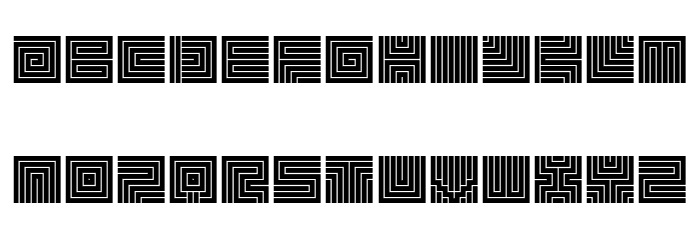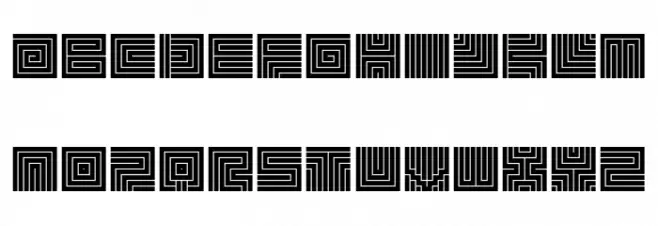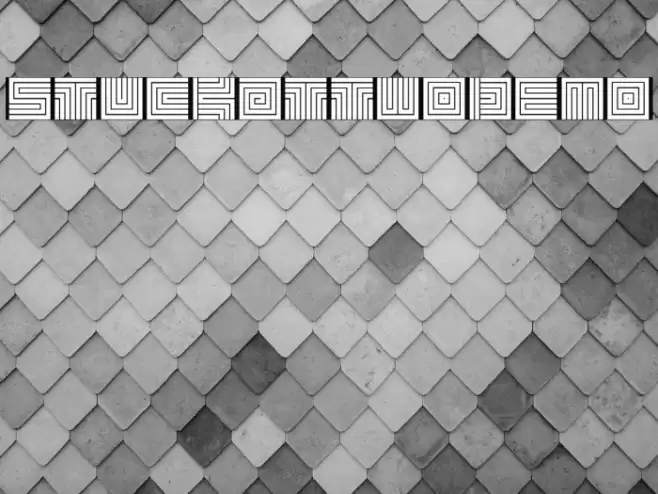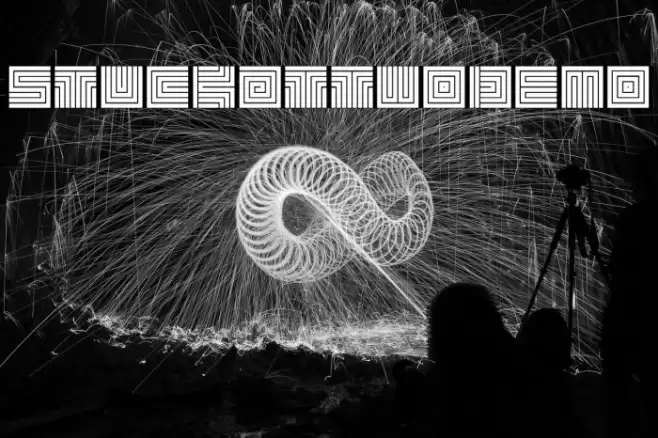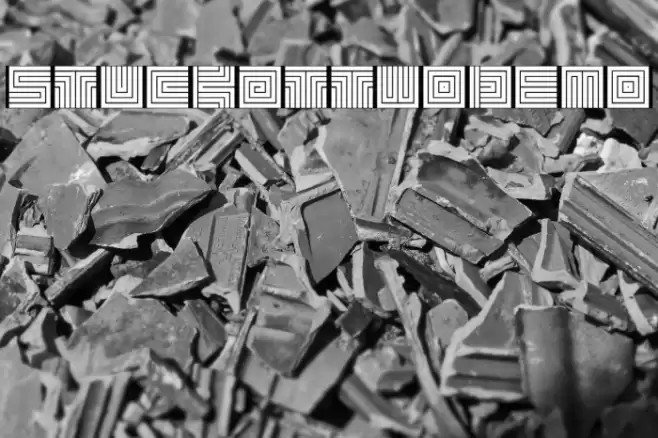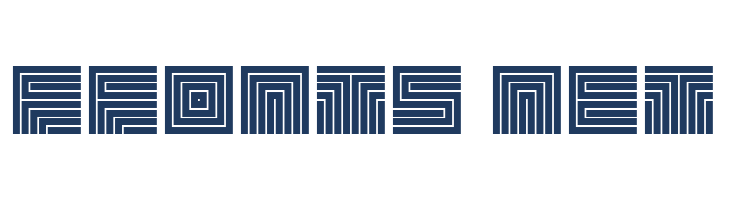
stuckattwo_demo1 Font
| Proiecte propuse | Ideal for use in modern art projects, branding for tech companies, futuristic designs, and eye-catching posters. |